השאלון עם עדי עובדיה
הכירו את עדי עובדיה – מעצב עצמאי, יליד 1997, במקור מעומר שבדרום וכיום תל־אביבי טרי. הוא חי בעיר יחד עם בן־זוגו ושני החתולים שלהם, סמי וחביבה. עם סיום לימודיו בתקשורת חזותית בבצלאל, החל לעבוד כעצמאי ומתמחה במיתוג ובטיפוגרפיה. בין לקוחותיו ניתן למצוא את משרד החינוך, עיריית תל־אביב וארגונים חברתיים. עדי מספר שמה שהוא הכי אוהב בעיצוב הוא “שאין שני פרויקטים זהים – כל אחד הוא הזדמנות למשהו חדש.” כשאינו יושב מול המחשב, הוא שוחה, רוכב על אופניים ברחבי העיר או יושב עם ספר ביד אחת וכוס אפרול בשנייה.
היי עדי, איפה אתה עובד עכשיו?
אחרי שסיימתי את הלימודים ועברתי לתל־אביב, עזבתי את העבודה בסטודיו שרון שרם, שם עבדתי במשך שנתיים במקביל ללימודים. מאז אני עצמאי, ועובד על פרויקטים עם לקוחות כמו משרד החינוך, עיריית תל אביב וארגונים חברתיים, ובין לבין עושה עוד פרויקטים בעולמות המיתוג והתרבות
אתה מעדיף לעבוד לבד או בצוות?
לא טוב היות האדם לבדו – אני אוהב להיות מוקף בחברים וקולגות שאני אוהב 🙂 אני מאמין שהרעיונות הכי טובים מגיעים מתוך שיחות ואינטראקציה עם אנשים אחרים, אבל כמובן שיש גם רגעים ופרויקטים שבהם כיף לעבוד לבד ולצלול לתוך העבודה.
על איזה פרויקט מעניין עבדת לאחרונה?
עבדתי עכשיו על פרויקט מרגש – יצירת שפה גרפית לסרט דוקומנטרי על מלכת הדראג האמריקאית Peppermint. עבדתי עם היוצר אוריאל פאר על עיצוב אריזה גרפית לכל הסרט לקראת הבכורה שלו בפסטיבלים בחו"ל – עיצבתי כמובן פוסטר לסרט, כמו גם טייטלים, רולר, תיק עיתונות וכו’
מה הדבר הכי טוב שקרה לך השנה?
למדתי לשחות!
מה אתה עושה כשאין לך מוזה?
עובד בלי מוזה.
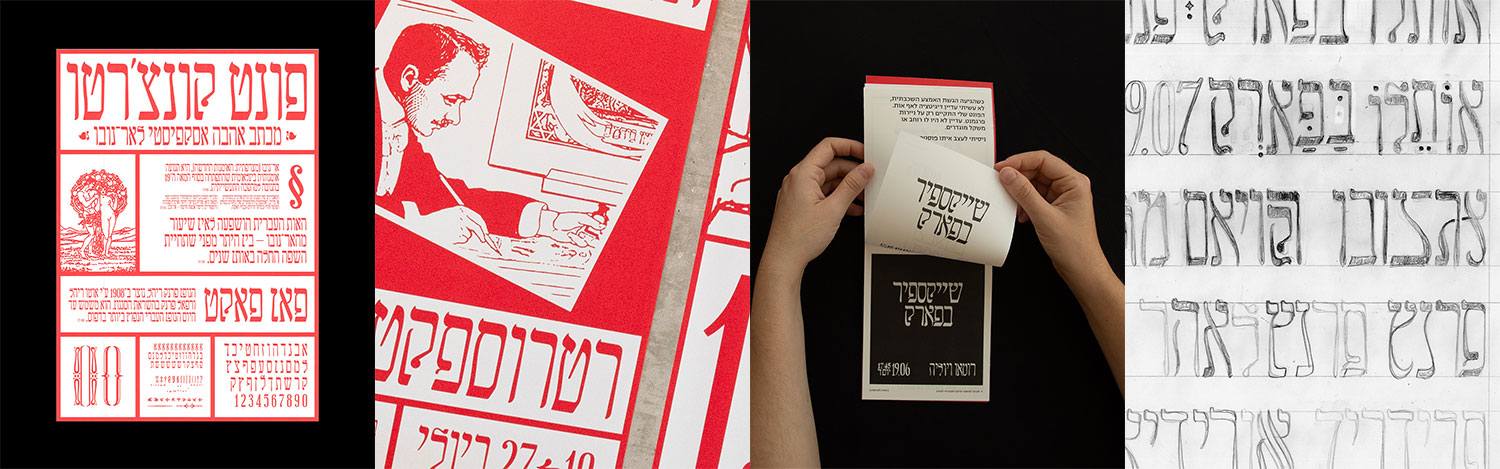
פרויקט הגמר של עדי עובדיה, ״קונצ׳רטו״, שנעשה בהנחיית דן עוזרי ודנה גז, הוא פונט שהוא מכתב אהבה לסגנון האר־נובו – חגיגה של קיטש ונוסטלגיה. הפרויקט נולד מתוך רצון ליצור משהו עשיר, סגנוני ורגשי דווקא בתקופה של חוסר ודאות, והוא שימש עבור עדי כמפלט יצירתי בזמן המלחמה. הוא יצר סדרת פוסטרים גדולים, אדומים ובולטים שאינם מתנצלים, כדי להציג את הפונט במלוא עוצמתו. לצד הפוסטרים, נלווה נספח מחקרי המספק הצצה להשראות, לסקיצות ולמסע האישי והעיצובי שעבר בתהליך. כיום ניתן למצוא את הנספח בספריית העיצוב בבית אריאלה.
מה אתה עושה בשביל הכיף?
בשנה האחרונה גיליתי את שני הדברים שמחזיקים אותי ביום יום: שחייה ורכיבה על אופניים. בגלל שאני עובד מהבית, אני מרגיש את הצורך לצאת ולזוז יותר מתמיד ואין כמעט יום שבו לא יצאתי לרכיבה בעיר או לשחות בבריכה. זה מרגיע ומרומם את הנפש, במיוחד אם אני הולך עם בן־זוגי שיחיה.
מה משך אותך לתחום?
דודה שלי, שגרה בצרפת, למדה תקשורת חזותית. מאז שאני זוכר את עצמי היא שולחת לי ספרים יפים, איורים, סקצ’בוקים ודברי פרינט בין הביקורים שלה בארץ. כשהיא הייתה בלימודים היא גם איירה לי ולאחים שלי ספרונים שאהבנו מאוד.
איזה מרצה השפיע/ה עליך במיוחד?
בשנה ג’ למדתי אצל דניאל גרומר קורס לטרינג שהיה מאוד משמעותי עבורי להמשך התואר והעבודה כמעצב ויוצר. בשנים א’–ב’ העיסוק בטיפוגרפיה היה מאוד מובנה ו"נכון". היה לי קשה להשתחרר מהחוקים והמגבלות שלמדנו, מתוך הכבוד והאהבה הגדולים שלי לטיפוגרפיה ובמיוחד לשפה העברית. דניאל לימד אותי לגשת לאותיות באופן קליל יותר, לא לקחת את כל העניין יותר מדי ברצינות, להשתטות לפעמים ולהרשות לעצמי ליצור מתוך הנאה.
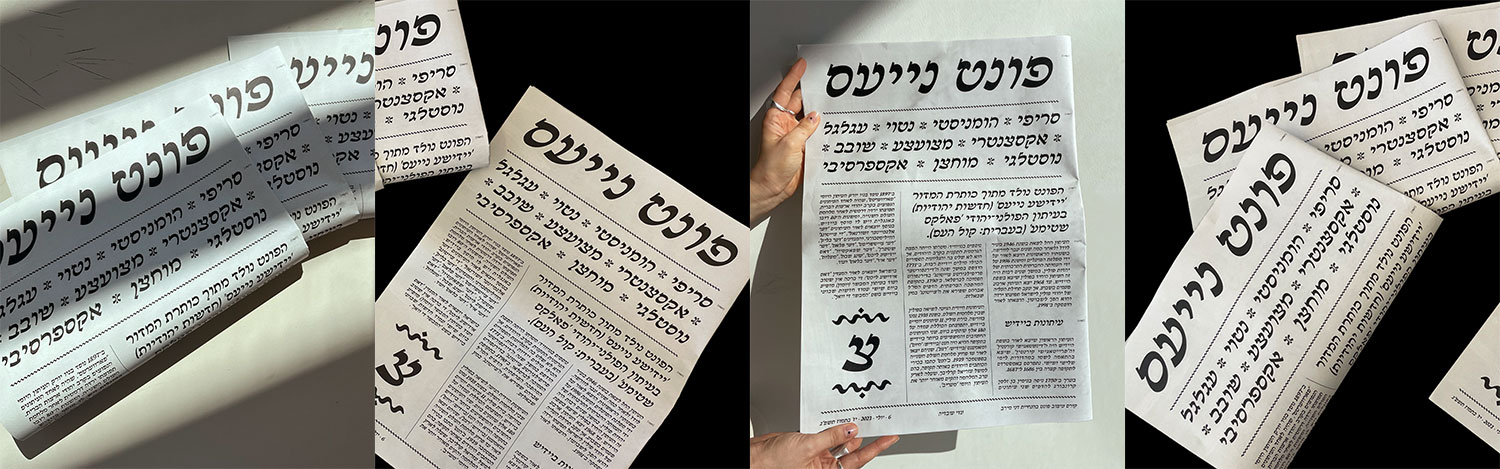
הפונט הראשון שעדי עיצב הוא ״נייעס״, פרויקט שנעשה במסגרת קורס עיצוב פונטים בהנחיית דני מירב (הטייס). ההשראה לפונט נולדה מכותרת במדור ״יידישע נייעס״ – חדשות יהודיות בעיתון יהודי־פולני ישן. מתוך חיבור להיסטוריה ולטיפוגרפיה יהודית מסורתית, ניסה עדי להפוך את ההשראה לאותיות חיות ובעלות אופי עכשווי. זו הייתה ההתנסות הראשונה שלו בעולם עיצוב הפונטים – הניסיון הראשון להפוך רפרנס טיפוגרפי למערכת שלמה, עובדת ונושמת.
ספר פרוזה או עיון אחרון שקראת
אני לא קורא המון אבל משתדל לקרוא יותר. הייתי לא מזמן בחופשה בצרפת, שבה קראתי את “תקלה בקצה הגלקסיה” של אתגר קרת – אני אוהב סיפורים קצרים, אבל בן־זוגי אוהב בדיוק את ההפך וממש עכשיו התחייבתי לקרוא יחד איתו את ״איליאדה״ של הומרוס (ואחריה את ״אודיסאה״) – תאחלו לי בהצלחה!
בהצלחה! רוצה להמליץ על ספר עיצוב?
זה לא ספר עיצוב פר אקסלנס, וקצת קשה להשיג אותו היום, אבל אני חייב להמליץ על ״ספר הכתב העברי״ של עדה ירדני. אחרי ארבע שנים של דפדוף בעותק שיש בספריית בצלאל, בן זוגי השיג לי עותק ממכירת עיזבון של סופר סת"ם, וזו הייתה אחת ממתנות יום ההולדת הכי מרגשות שקיבלתי.
אתר השראה מדליק שאנחנו לא מכירים
אני אוהב לשוטט ולראות מה חדש באתר Site Of Sites – יש שם דוגמאות לאתרים מכל מיני סוגים שגורמים לי לרצות לעצב עוד אתרים בעצמי.
באיזה פונט אתה רוצה שיכתבו על המצבה שלך?
״הדסה״, ללא ספק. יש בו משהו ישראלי מאוד מצד אחד, רגיש מצד שני וקלאסי מצד שלישי.
יש לך המלצה מוזיקלית?
אני שומע בעיקר פופ ואוהב להאזין לדברים חדשים ברוח התקופה. בבית יש לי גם פטיפון עם כל מיני תקליטים שאספתי מפה ומשם.
קיצור מקלדת אהוב
Cmd+Z
כתוב בבקשה את המילה הבאה בכתב היד שלך: